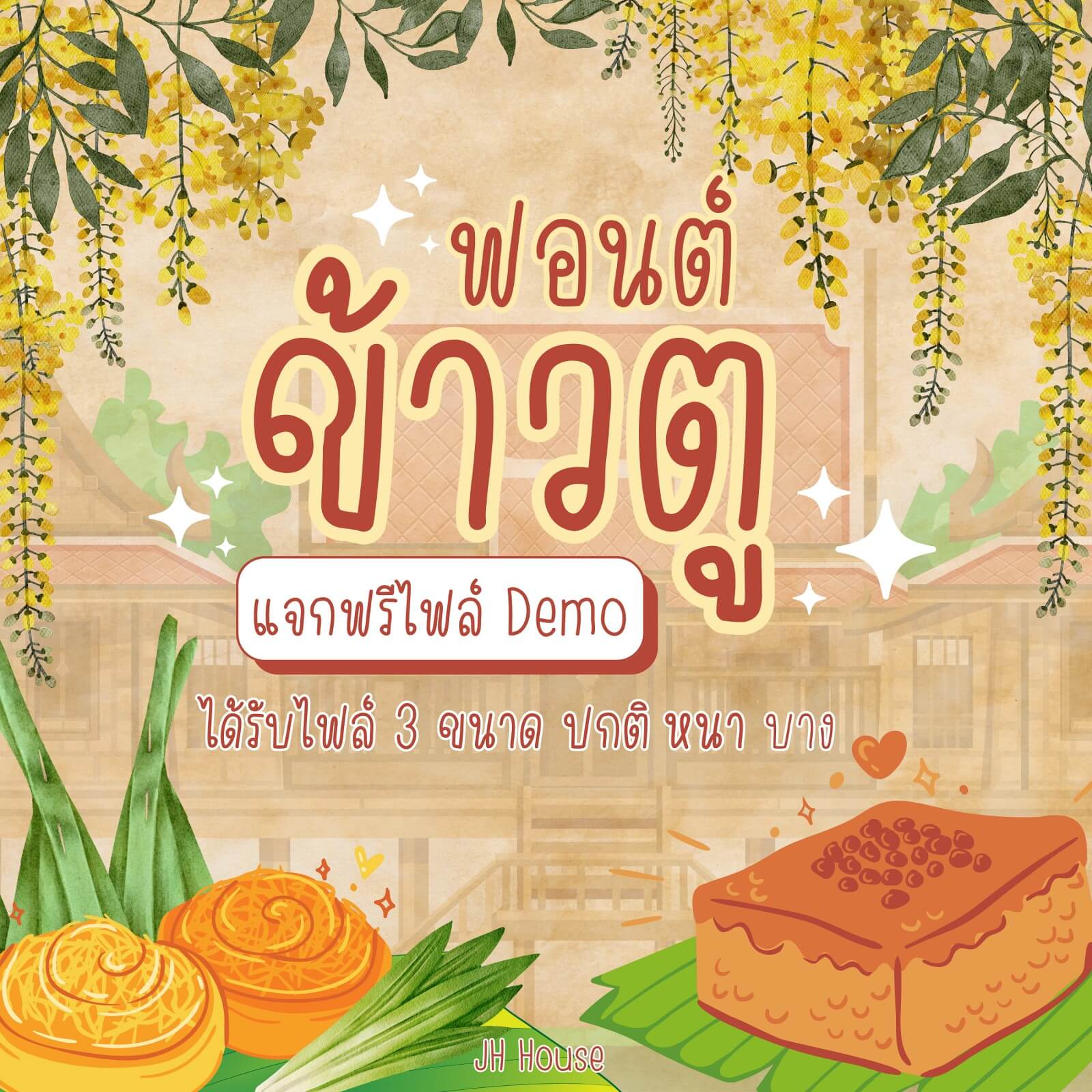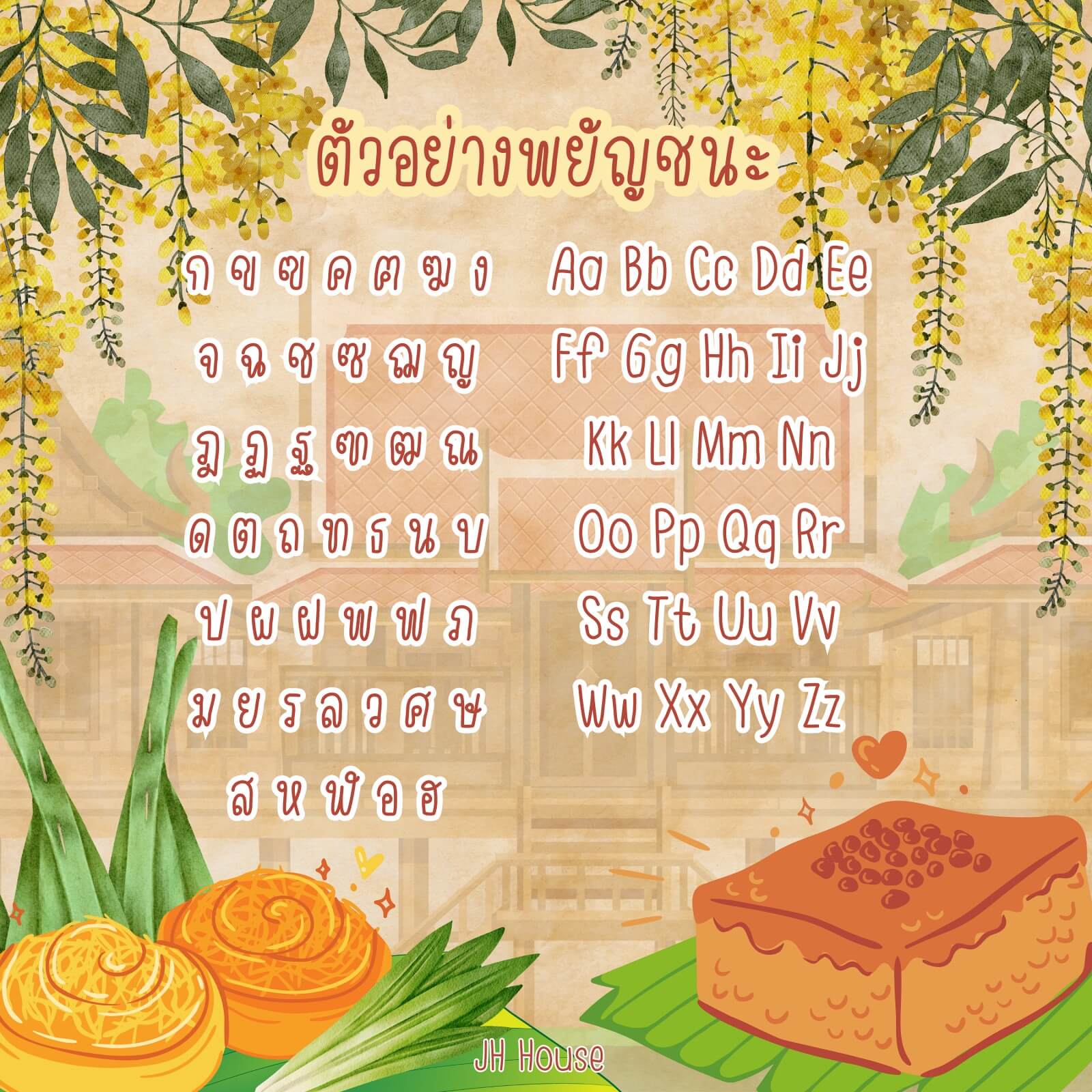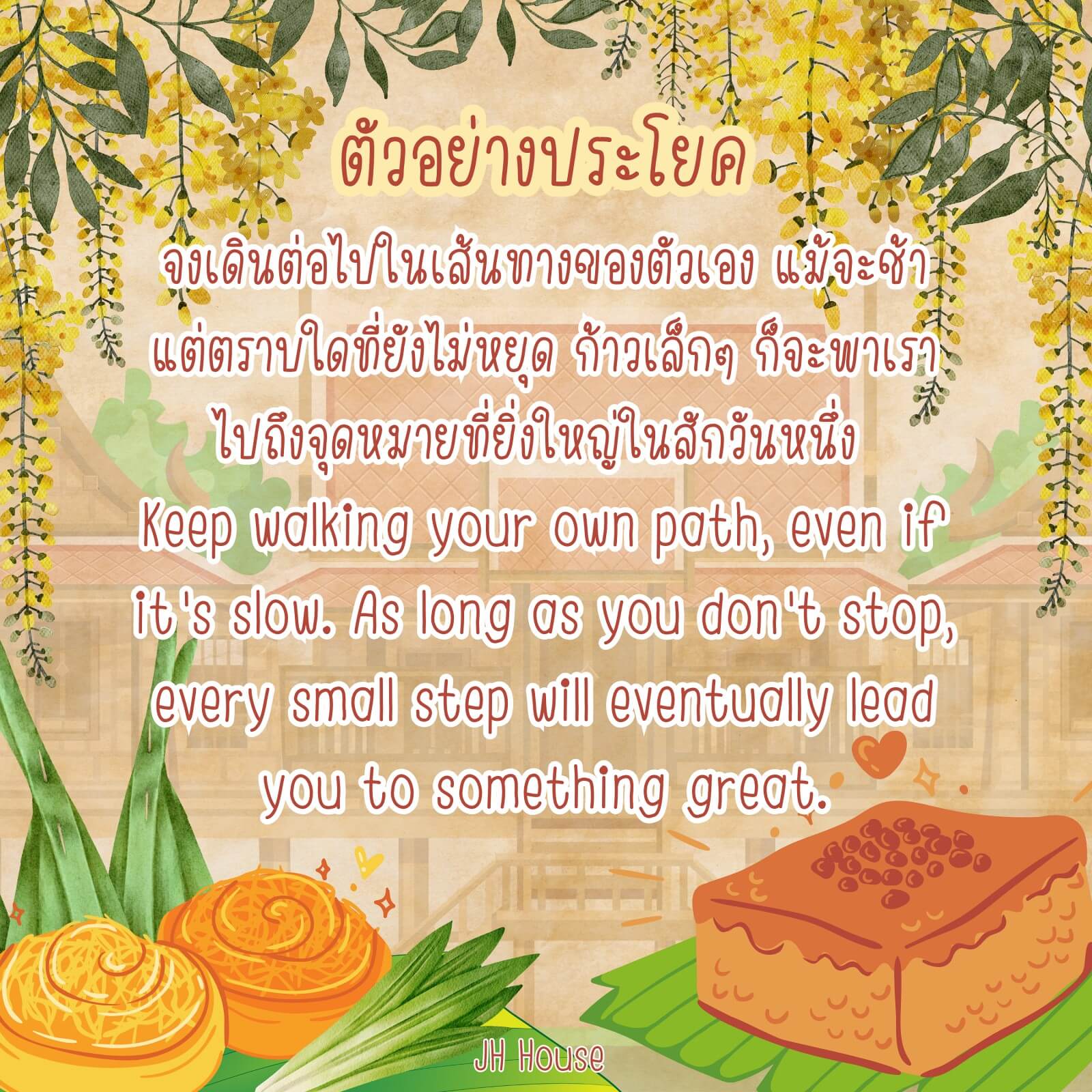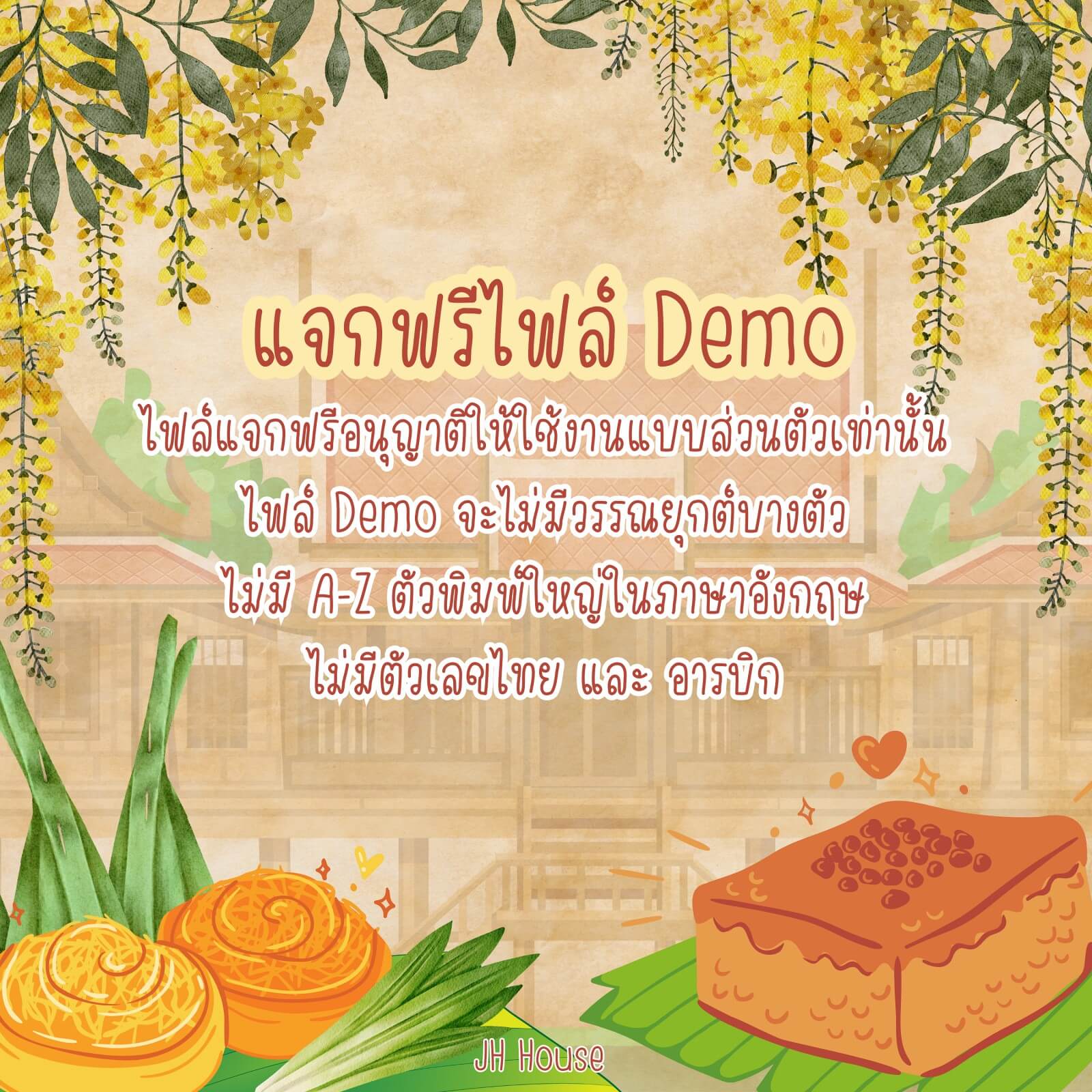
ฟอนต์ข้าวตู – ฟอนต์ลายมือ เหมาะสำหรับจดโน้ต จดสรุป รองรับทุกโปรแกรม ทุกแอปพลิเคชัน เช่น Canva, Capcut, Goodnotes, Ibis, Procreate, Photoshop ฯลฯ
ข้าวตู (JHKhaotu)